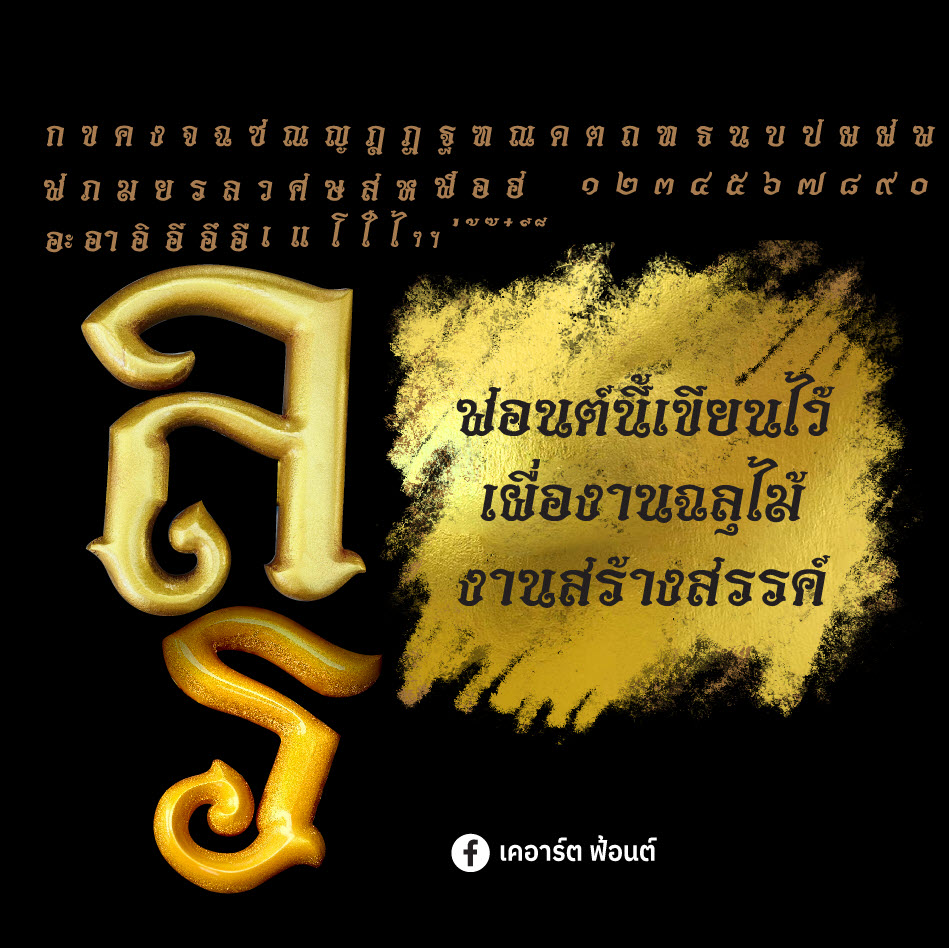
เคอาร์ตรามเกียรติ์ เป็นฟอนต์งานไทยที่ใช้เวลาเขียนนานพอสมควรเป็นงานยากสำหรับงานหลบหางอักษรเขียนแก้มานับไม่ถ้วน
เวอร์ชั่นนี้เป็นเดมโม่อยากให้ทดลองใช้กันครับ โดยเขียนให้ใช้งานป้ายได้ด้วยโดยเฉพาะงานฉลุอักษรงานไม้ CNCงานป้ายอักษร
ชื่อฟอนต์ : แนวไทยโบราณ (Kart-Ramakien-demo)
สร้างสรรค์โดย : เคอาร์ตฟอนต์